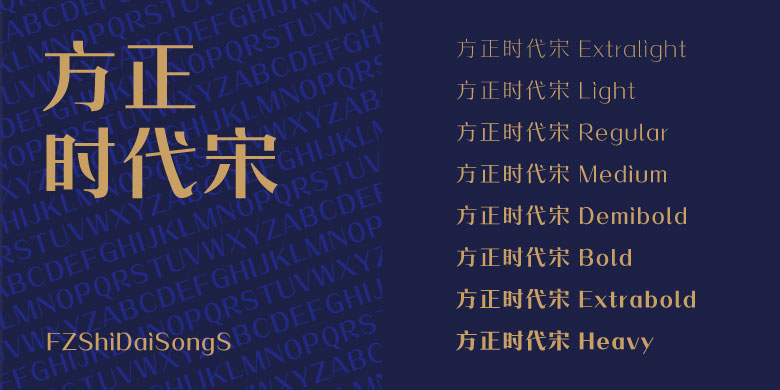
方正时代宋家族
方正时代宋家族,这款字体结构工整、笔画清晰,兼顾美观与易读性,适用于标题、正文、海报、包装、LOGO 等多种场景。字形优雅稳定,风格百搭耐看,适配日常排版与创意设计,让文字呈现更舒适、更具质感。方正时代宋家族一笔一画,皆是细节,以均衡的比例、流畅的线条打造舒适视觉体验,字形端正大气,风格简约现代。无论是商业设计、品牌宣传还是日常排版,都能轻松驾驭,让文字更有格调与力量。方正时代宋家族字体下载。
郭炳权先生的佳作“雅兰体”,在2015年纽约TDC文字设计大赛中获奖。“时代宋”则是把“雅兰体”设计手法和“宋体”进行了有机融合。它既有着传统宋体的印象,也有雅兰体的韵致,体现了字体的时代感,让人耳目一新。作为一款商业百搭字体,“时代宋”有8个不同粗细,适合各类商业宣传和包装设计。